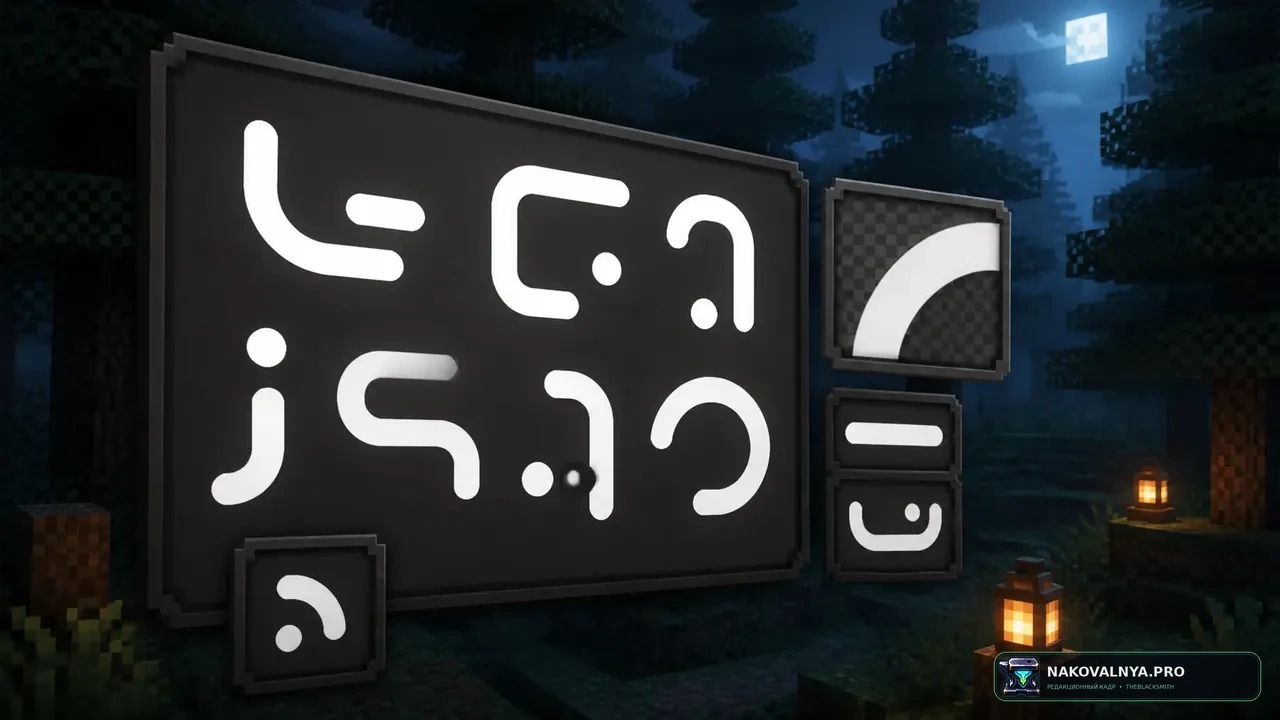
Font++ — текстуры на гладкий шрифт с десятикратным разрешением в МайнкрафтеВ стандартном пиксельном шрифте наклонные штрихи строятся заметными ступенями. Font++ повышает разрешение в десять раз и использует дополнительную детализацию, чтобы сгладить контуры. Особенно наглядны A и X: их диагонали выглядят как настоящие наклонные линии. При этом проект остаётся лёгким и касается именно символов, а не фона меню или игровых текстур. Он подходит пользователю, который читает много английского текста и хочет более ровную типографику. Для оценки откройте чат, меню и книгу с разными размерами строк, затем отдельно проверьте поддерживаемую пунктуацию и знаки валют.
Поддерживаются только латинские буквы без диакритики, выбранные знаки пунктуации и символы валют. Акцентированные буквы и другие письменности не входят в заявленный охват. Каталог относит пакет к категории 512x+. На сервере не работает: ставится только на клиент.
Если часть текста осталась ванильной или выглядит иначе, сначала определите набор символов. Пакет не поддерживает акцентированную латиницу и другие алфавиты, поэтому смешанная строка закономерно может использовать разные формы. Не ожидайте полной коллекции пунктуации: заявлены только отдельные знаки. Другой шрифтовой ресурспак способен перекрыть Font++, поэтому оставьте один слой для диагностики. Высокая категория разрешения относится к шрифту и не означает, что блоки или GUI-фоны получили новые HD-текстуры.
Font++ делает поддерживаемую латиницу заметно более гладкой и аккуратной, сохраняя узкое назначение. Главный компромисс — ограниченный набор символов без акцентированных букв и других письменностей. Поэтому он действительно лучше всего подходит интерфейсу с простым английским текстом; в многоязычной сборке заранее проверьте все часто используемые длинные игровые строки, чтобы понять, насколько естественно рядом выглядят улучшенные и fallback-символы.
В десять раз относительно обычного.
Они отображаются настоящими наклонными линиями.
Только выбранная пунктуация и знаки валют.